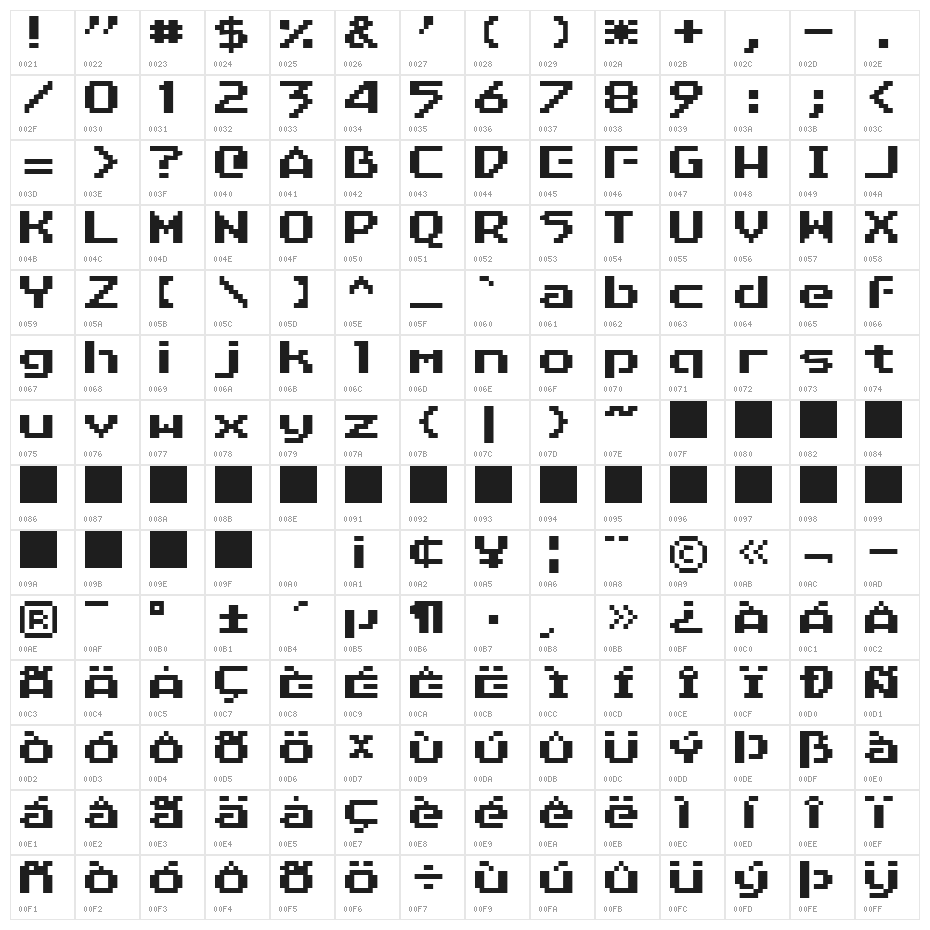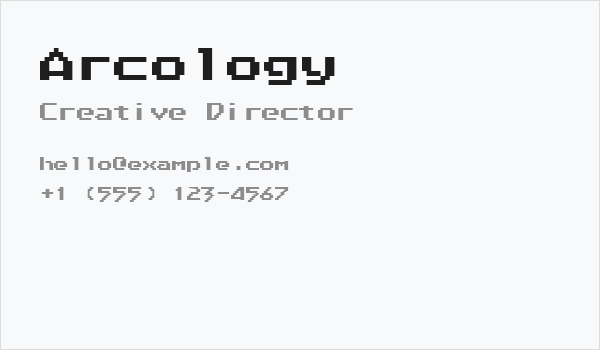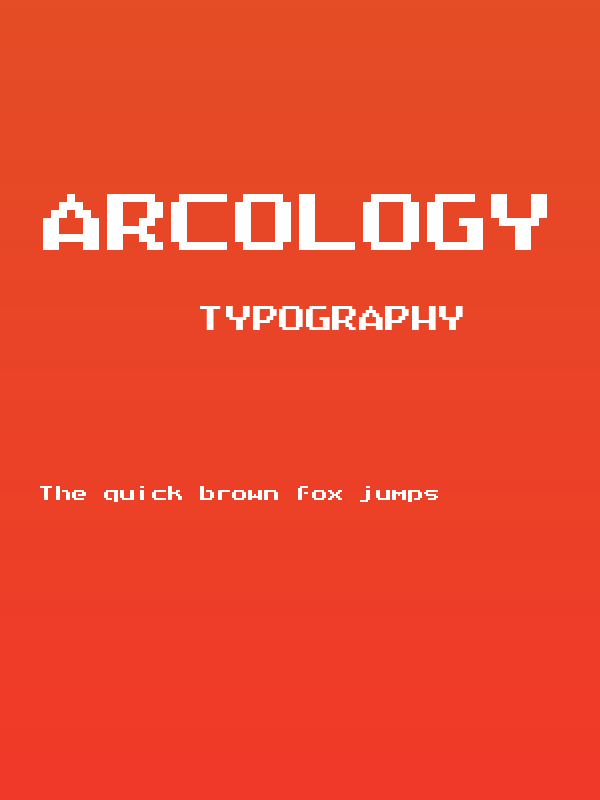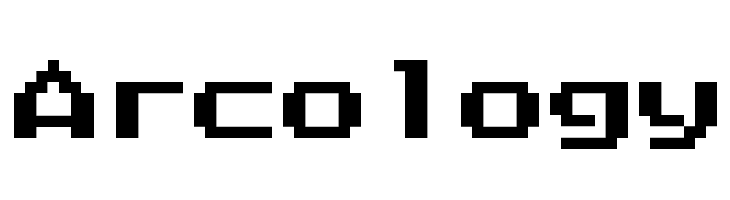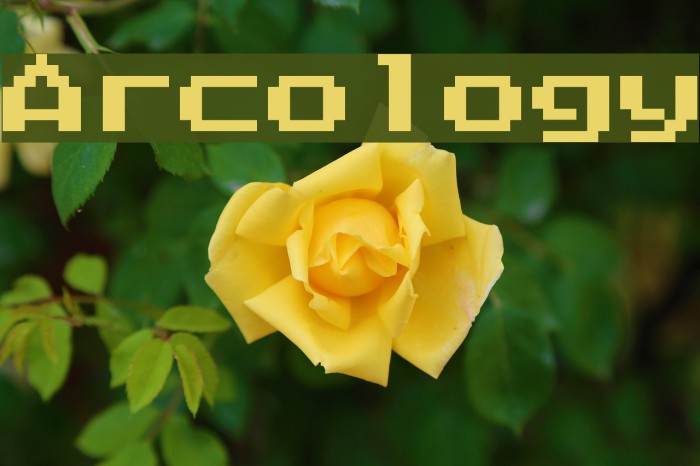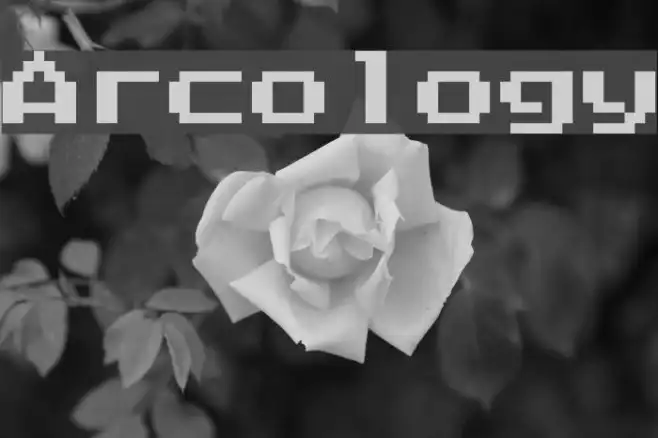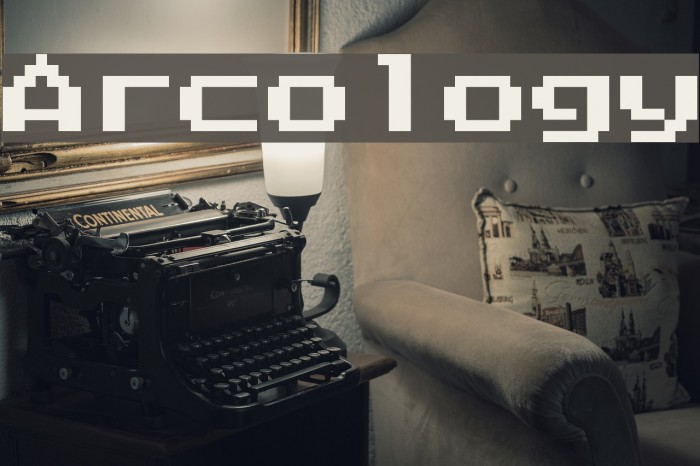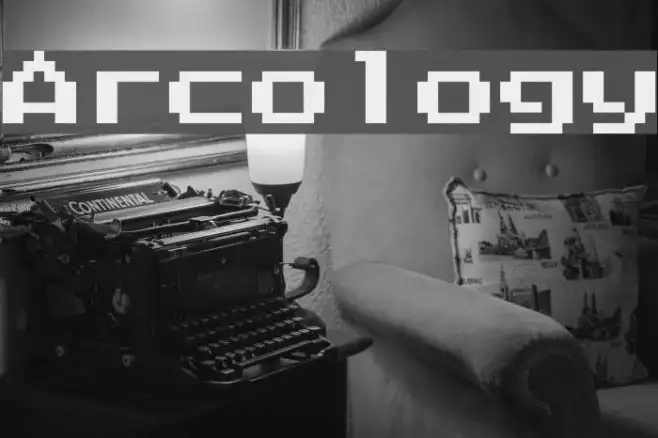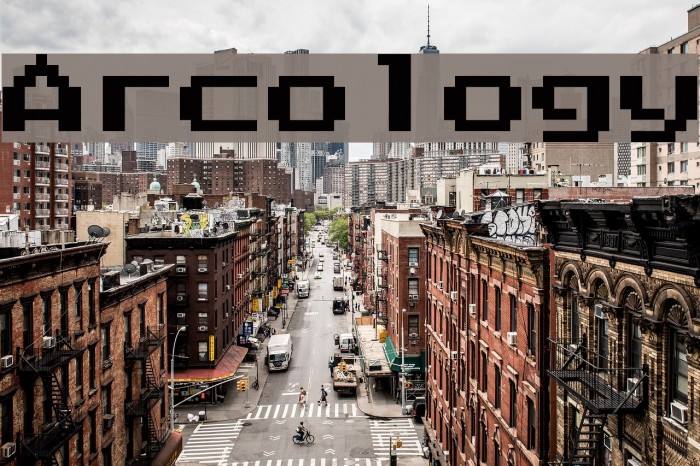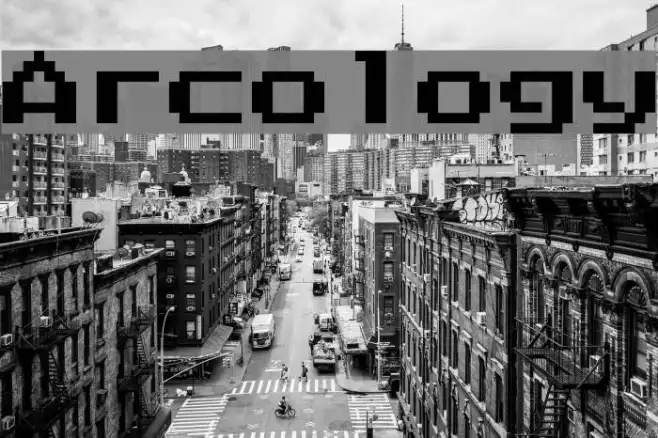
Arcology Font
✎ Pixel
| Estilo general | Retro, Digital |
| Caso de uso | Headlines, Logos, Digital Art |
| Proyectos propuestos | Ideal for video game designs, retro-themed posters, digital art projects, and any creative work that seeks to evoke nostalgia for early computing and gaming eras. |